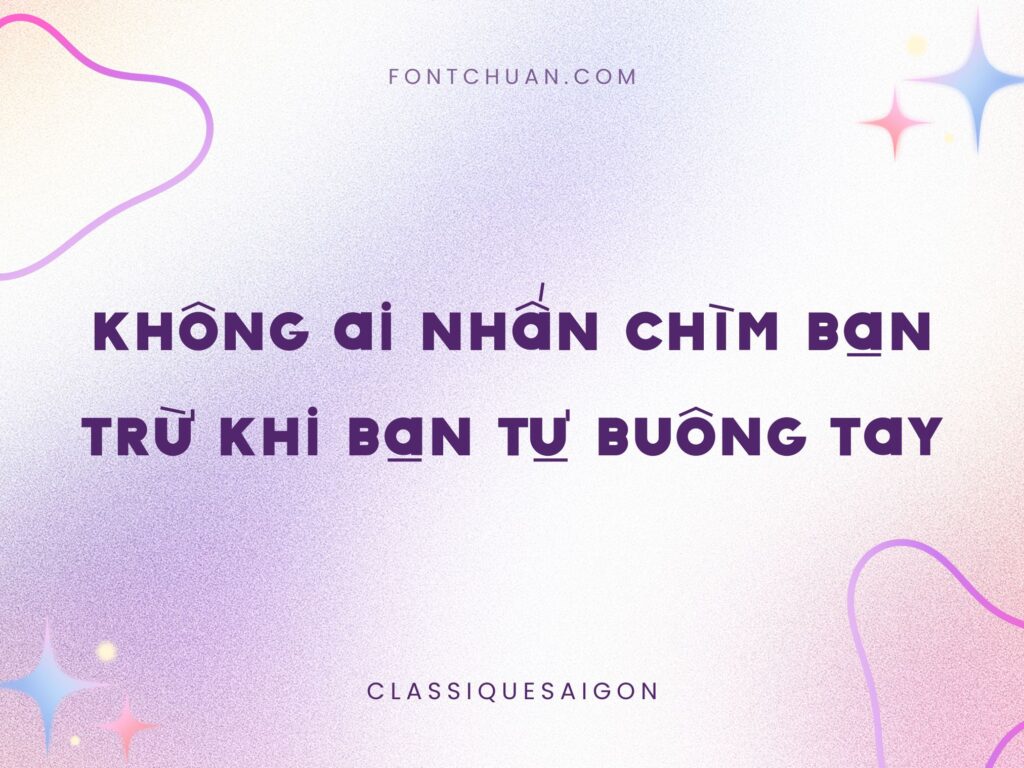
Font Classique Saigon Typeface Việt Hóa
Classique Saigon là một phông chữ sans-serif đậm chất hình học, được thiết kế bởi Mạnh Nguyễn, một nhà thiết kế phông chữ tại Việt Nam. Phông chữ này lấy cảm hứng từ các bảng hiệu và biểu ngữ vẽ tay cổ điển tại Việt Nam từ thế kỷ trước, đặc biệt là ở Sài Gòn. Classique Saigon kết hợp hài hòa giữa phong cách cổ điển và hiện đại, tạo nên sự độc đáo và thu hút cho các thiết kế. Phông chữ này hỗ trợ đa ngôn ngữ và miễn phí cho sử dụng cá nhân; nếu bạn muốn sử dụng cho mục đích thương mại, vui lòng kiểm tra giấy phép sử dụng hoặc liên hệ với tác giả để biết thêm chi tiết.
Nhờ thiết kế cân đối và tinh tế, Classique Saigon cũng có thể được sử dụng như một Font chữ thiệp cưới, giúp các nhà thiết kế tạo ra những tấm thiệp cưới vừa sang trọng vừa đậm chất cổ điển, đồng thời vẫn giữ được sự hiện đại và dễ đọc trong từng nét chữ.